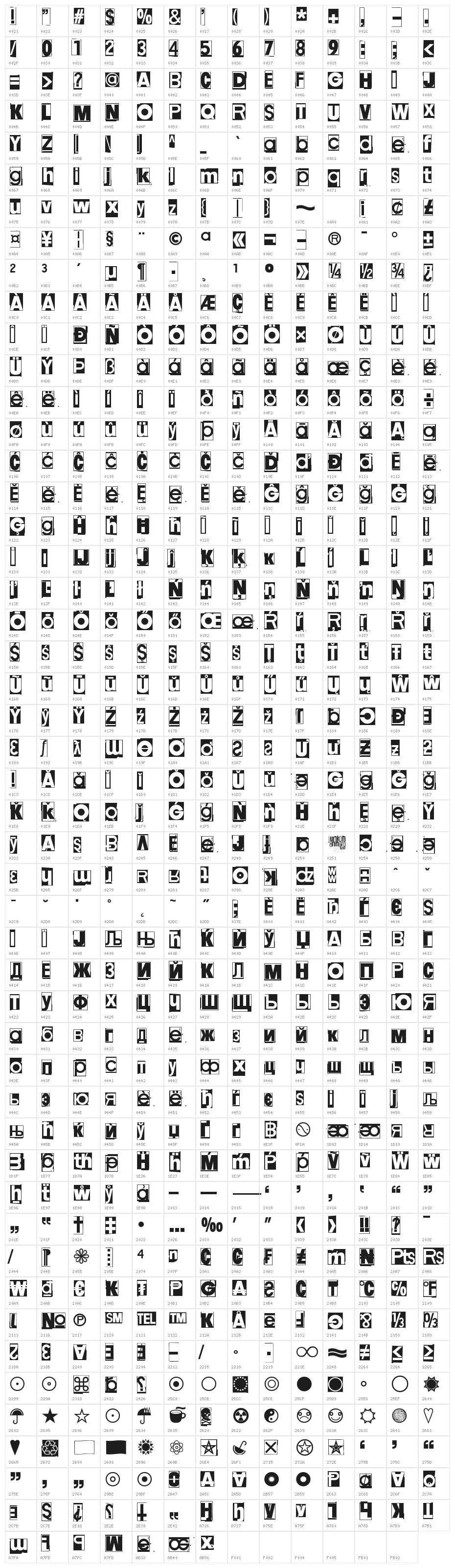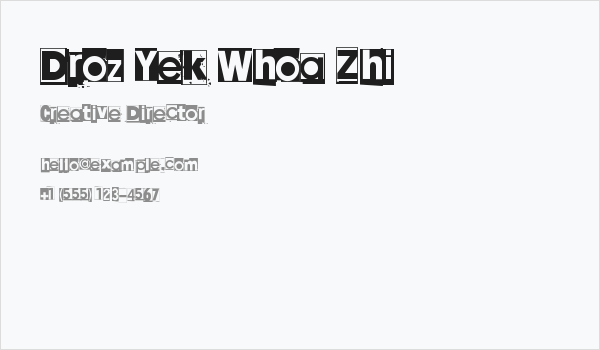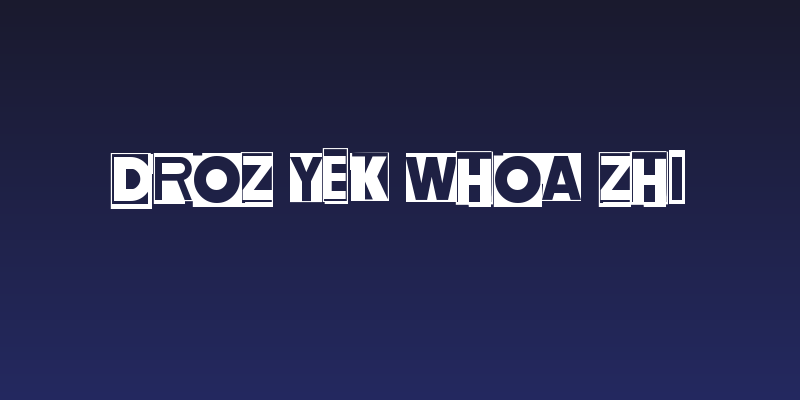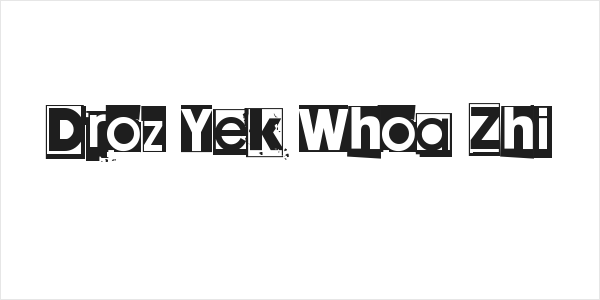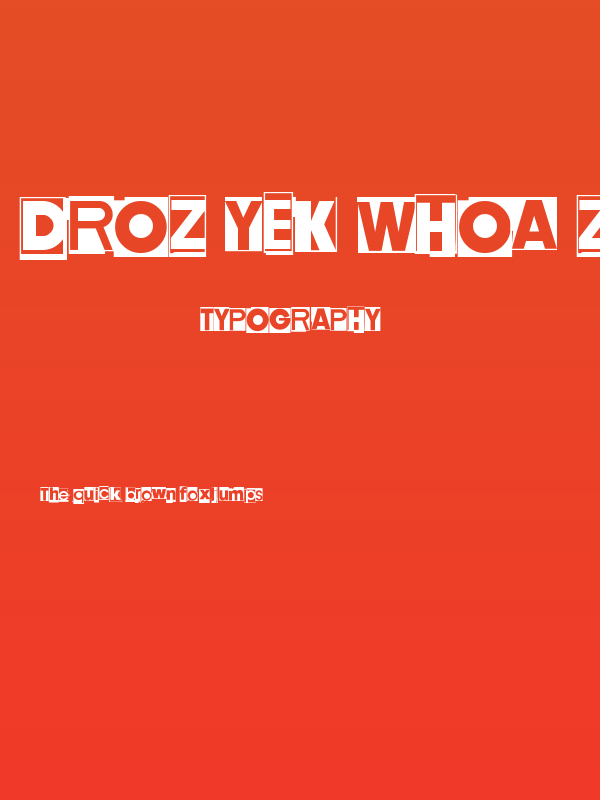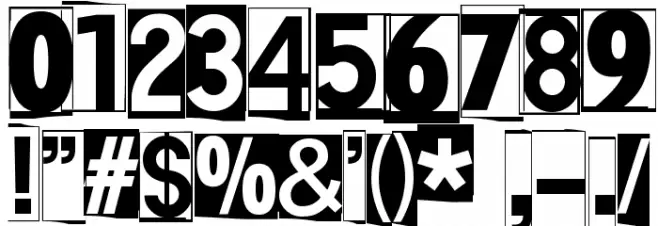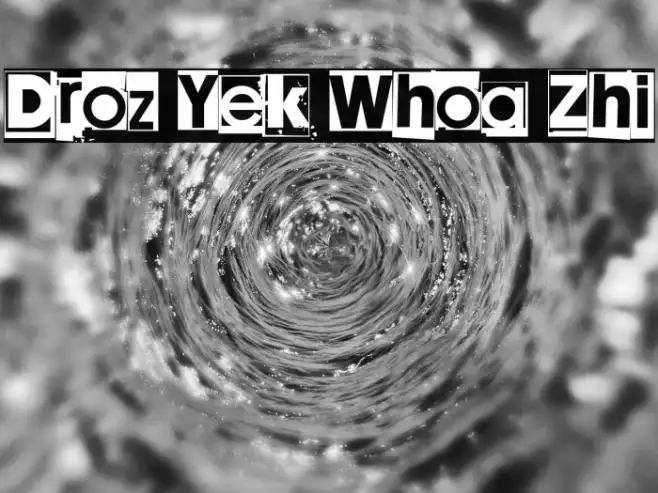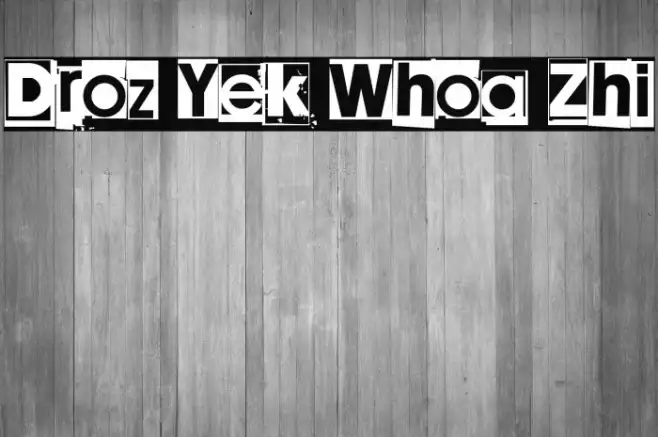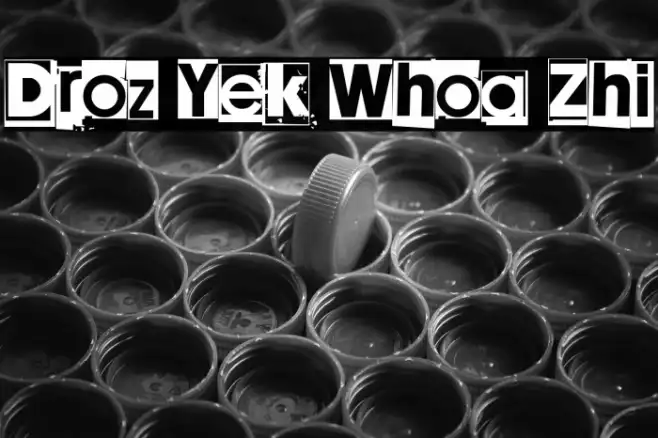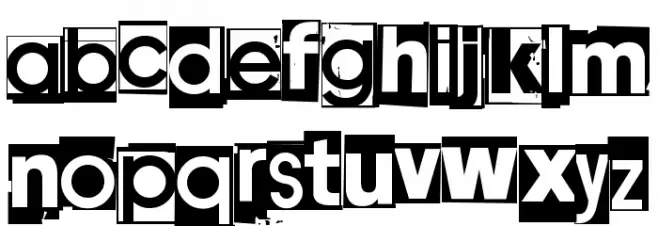
Droz Yek Whoa Zhi Font
| Gesamtstil | Modern, Artistic |
| Vorgeschlagene Projekte | Ideal for creative projects such as posters, album covers, and branding that require a bold and artistic touch. |